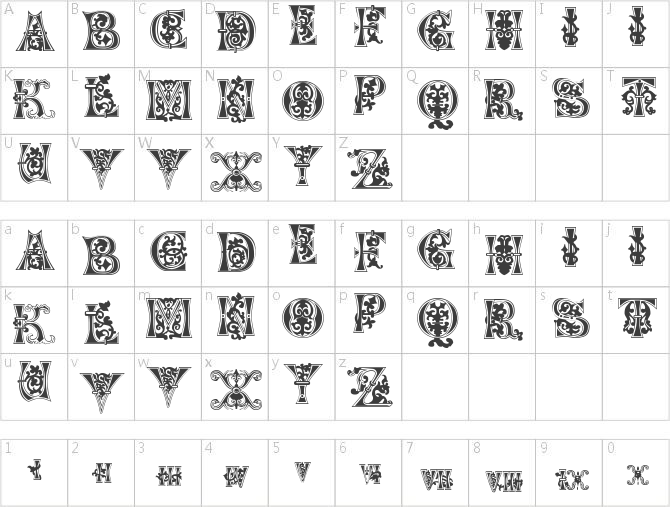
FloralMajuscules
FloralMajuscules介绍
FloralMajuscules字体字库是一款让人赏心悦目、百看不厌的英文字体,适合各类广告和产品包装设计应用,字体大小0.17MB,格式为ttf字体,上传用户是373790005,作者/版权方为未知
FloralMajuscules效果图